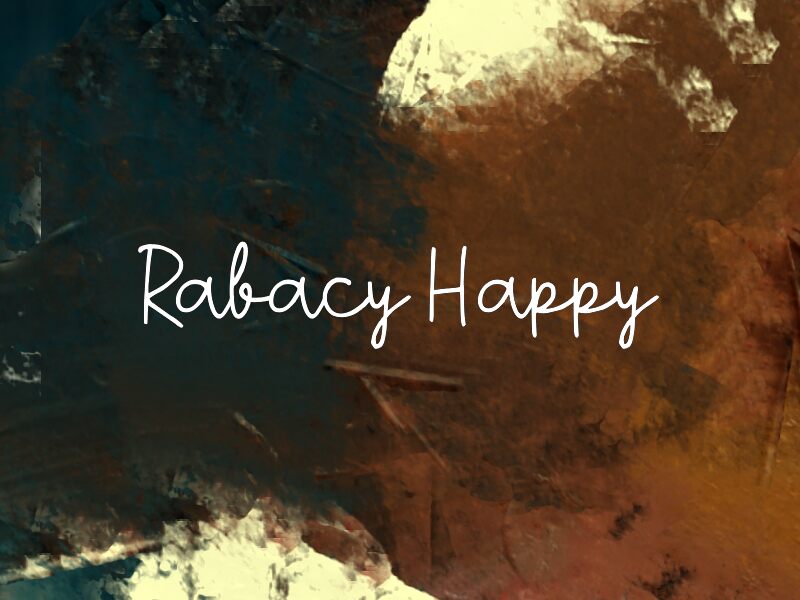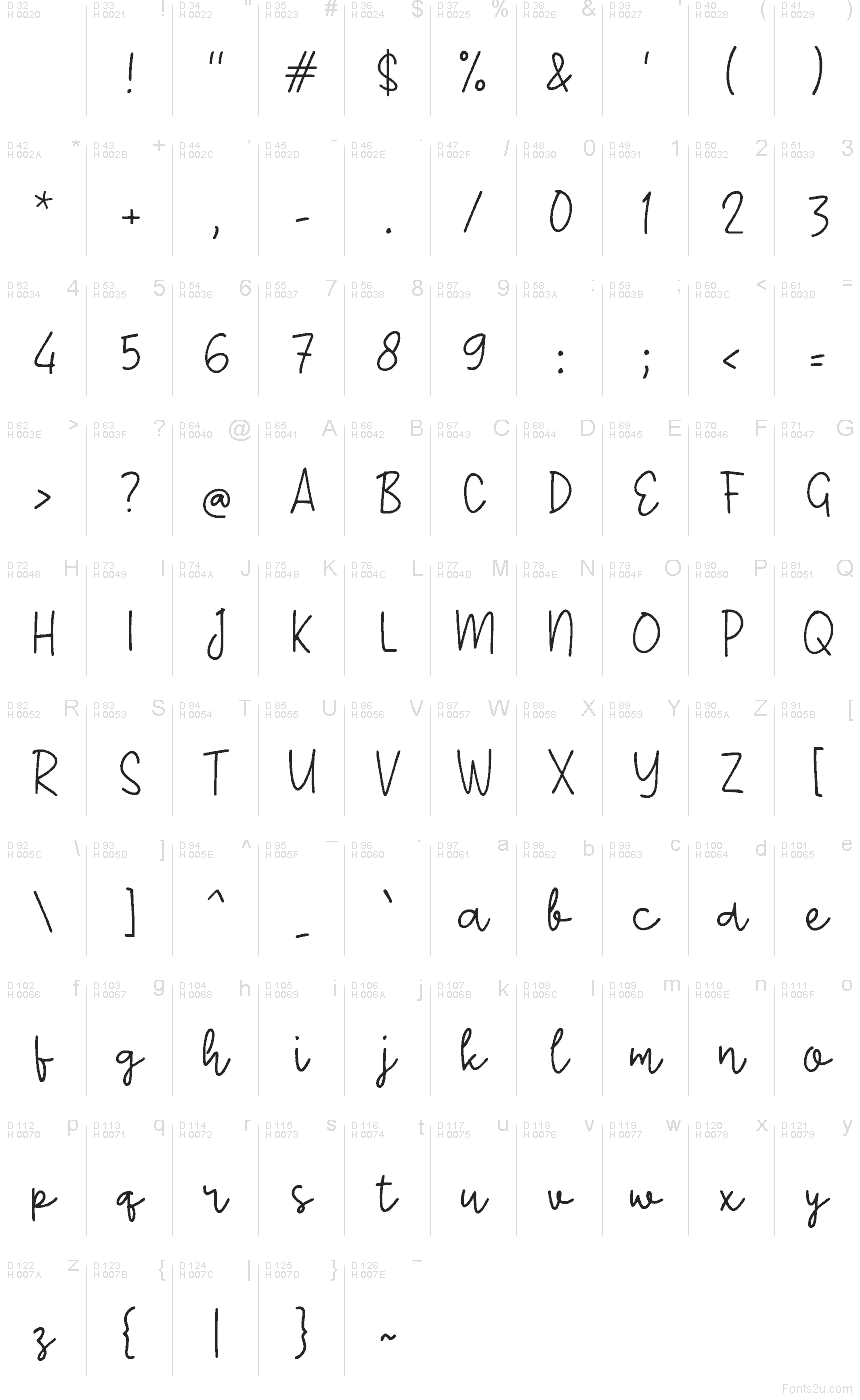
Rabacy Happy
Rabacy Happy di Wep è un font scritto a mano, giocoso e dal ritmo sciolto e solare. Le lettere richiamano il tratto di un pennarello, mescolando tratti lunghi e curvilinei con forme larghe e rotonde, per un risultato fresco e amichevole, lontano da uno stile troppo rigido o rifinito.
Si adatta perfettamente al branding di caffetterie, copertine di libri per bambini, packaging allegri, titoli di scrapbook e card con citazioni sui social media, dove un font libero con così tanta personalità riesce a dettare il mood da solo. Usalo per titoli brevi, targhette o locandine di eventi se desideri che le forme sinuose e la spaziatura aperta aggiungano un tocco personale e leggero.